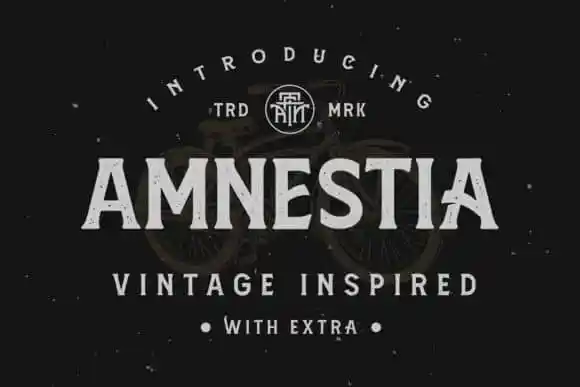
A Amnestia Display Font é uma elegante tipografia feita para quem busca um blend perfeito entre modernidade e sofisticação vintage. Este tipo de fonte foi criada a partir dos arredondados da serif clássica, inspirado nos antigos cartazes que marcaram décadas. Arterfak Project é o nome do designador da fonte, uma escolha cuidadosa para criar um sentido único e único. Com sua altura média perfeita para fins de exposição ou subtexto, a Amnestia oferece à criatividade muitas alternativas ao usar letras maiúsculas. São 100+ alternativas que lhe dão mais opções para gerar múltiplas variações em suas criações. Este é um tipo de fonte vintage serif com um toque moderno, uma combinação perfeita entre clássico e atual. Com um estilo desgastado, a Amnestia se destaca ainda mais como uma opção ideal para logomarcas, selos, roupas, etiquetas, embalagens, outdoors e muito mais. O seu design vintage em serif minimiza-se de forma minimalista, criando um estilo moderno. É perfeitamente adaptável a diversos contextos gráficos exigindo diferentes estilos, tornando-o uma escolha ótima para designers que buscam um equilíbrio entre clássico e contemporâneo.